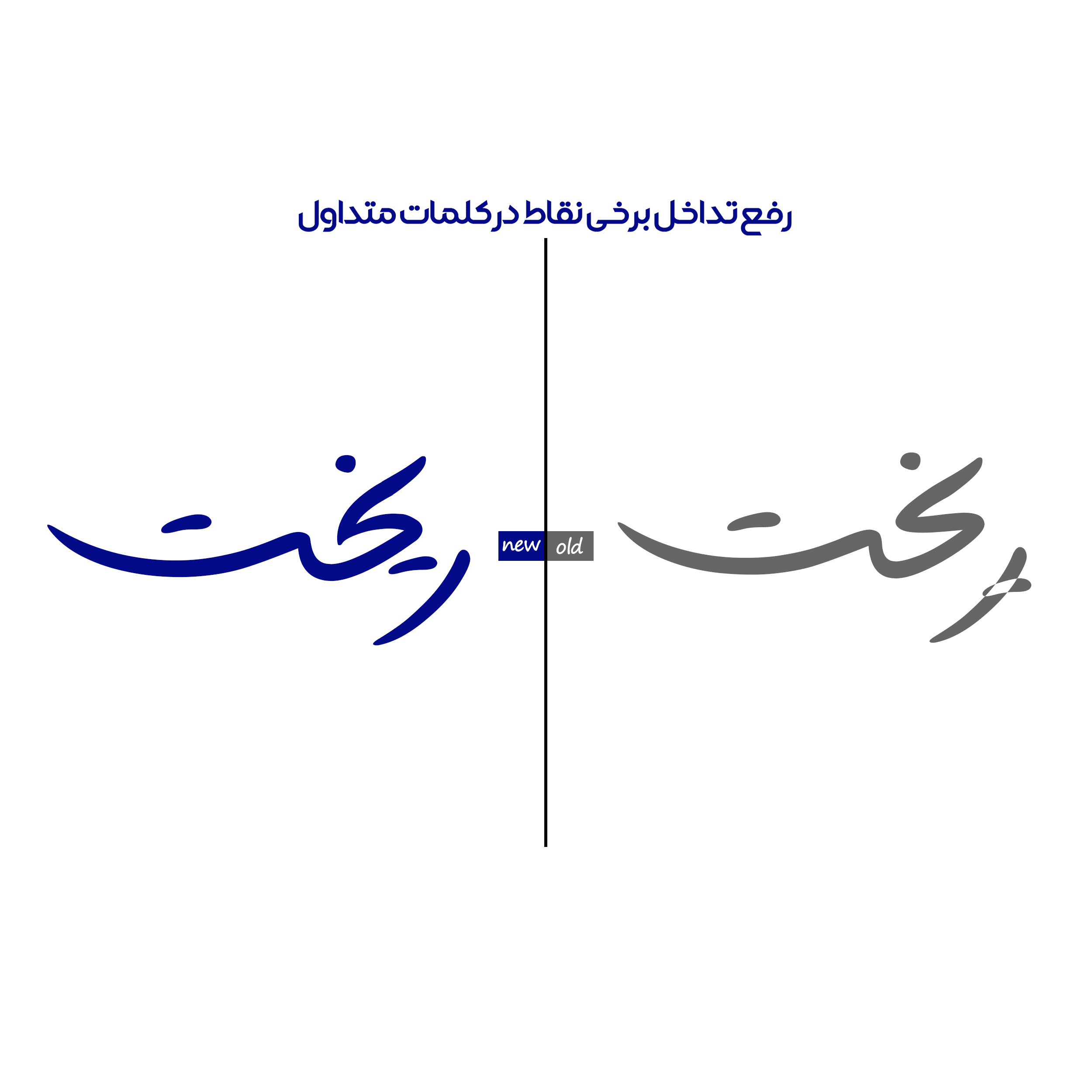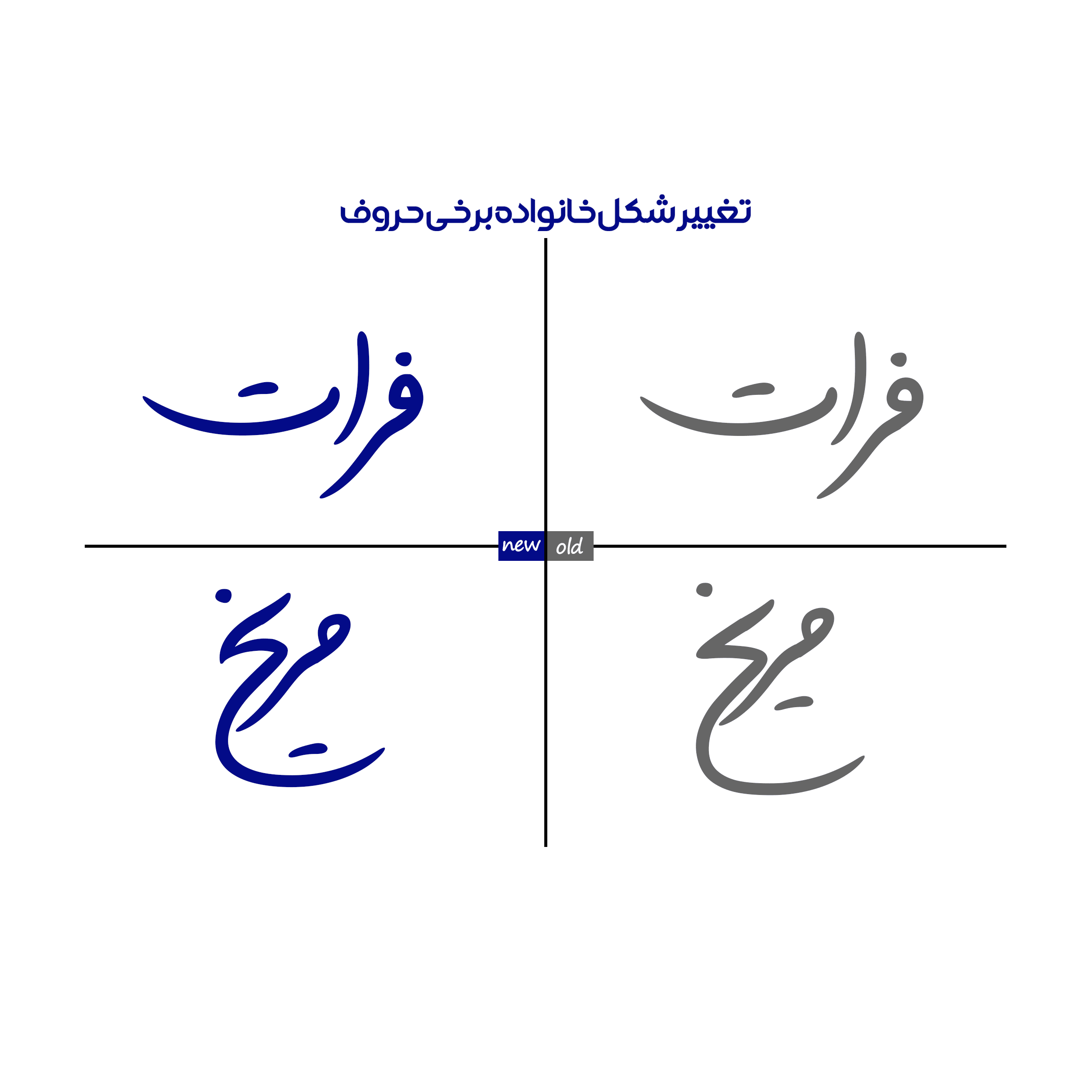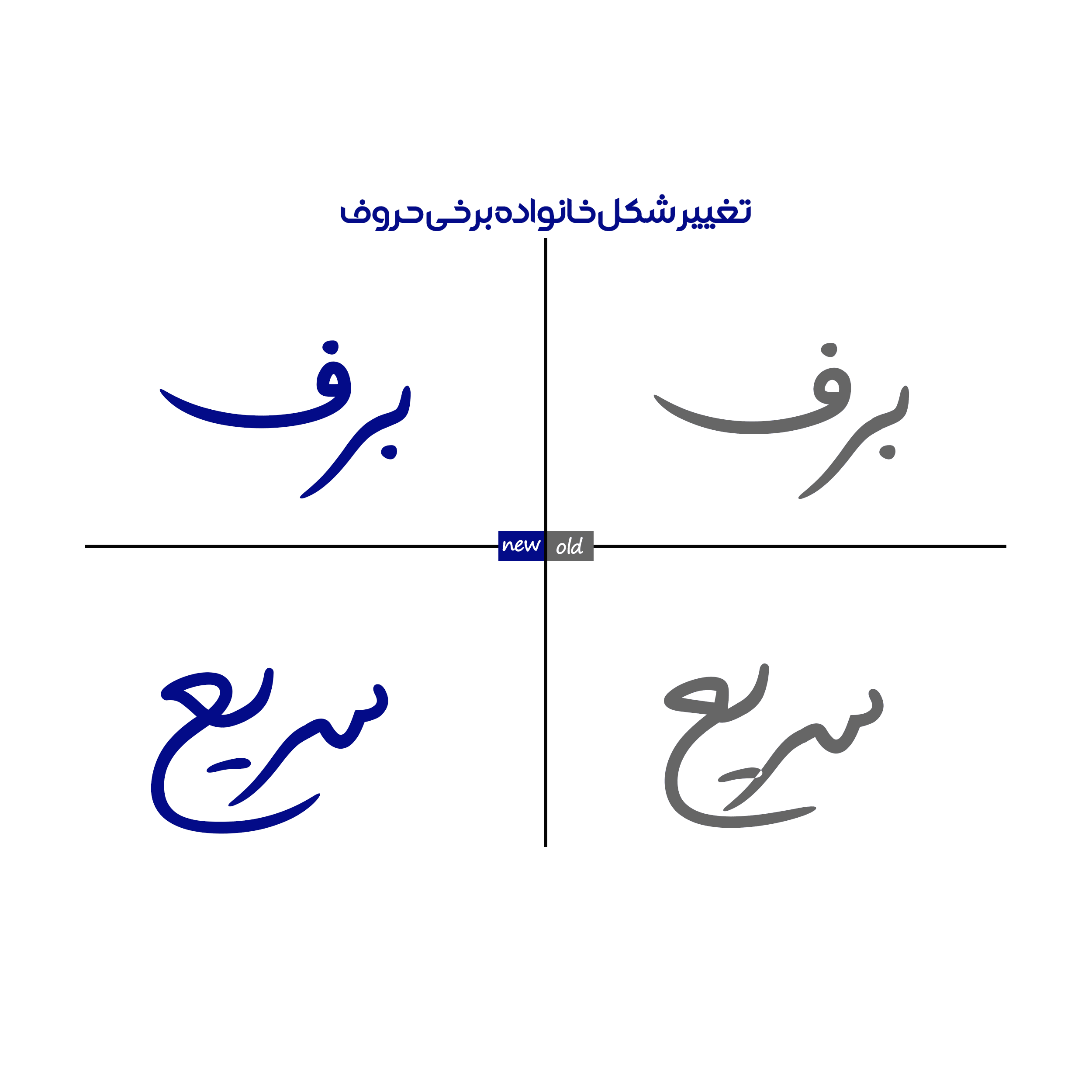
در فونت مانلی نسخه ۲.۵ چه مشکلاتی رفع شده است.
فونت مانلی از بهترین نمونه فونتهای دست نویس خودکاری است. فونت مانلی بسیار شبیه به دست خط طبیعی است و برای همین حس انسانی زیادی به نوشتهها میدهد.
فونت مانلی اپلین بار در سال ۱۳۹۷ منتشر شده است و بارها به روز رسانی شده است. محمد عمویی در نسخه جدید فونت مانلی مشکلات زیر را رفع کرده است و ترکیبات جدیدی را نیز به این فونت اضافه کرده است که باعث زیباتر شدن فونت مانلی میشود.
۱- رفع برخورد بعضی نقطهها با حروف
۲- تغییر شکل حروف در بعضی ترکیبات
۳- اضافه شدن ترکیبات جدید